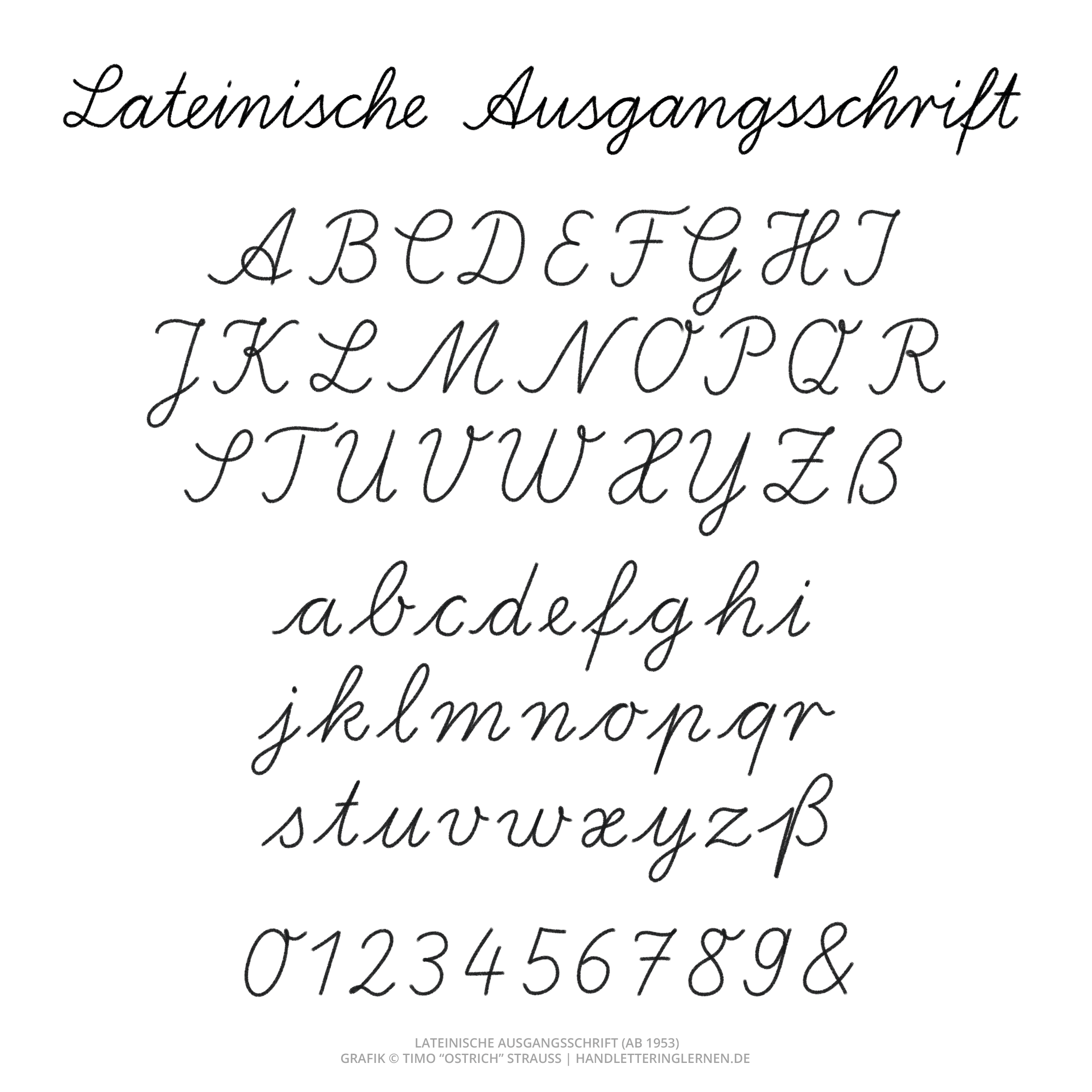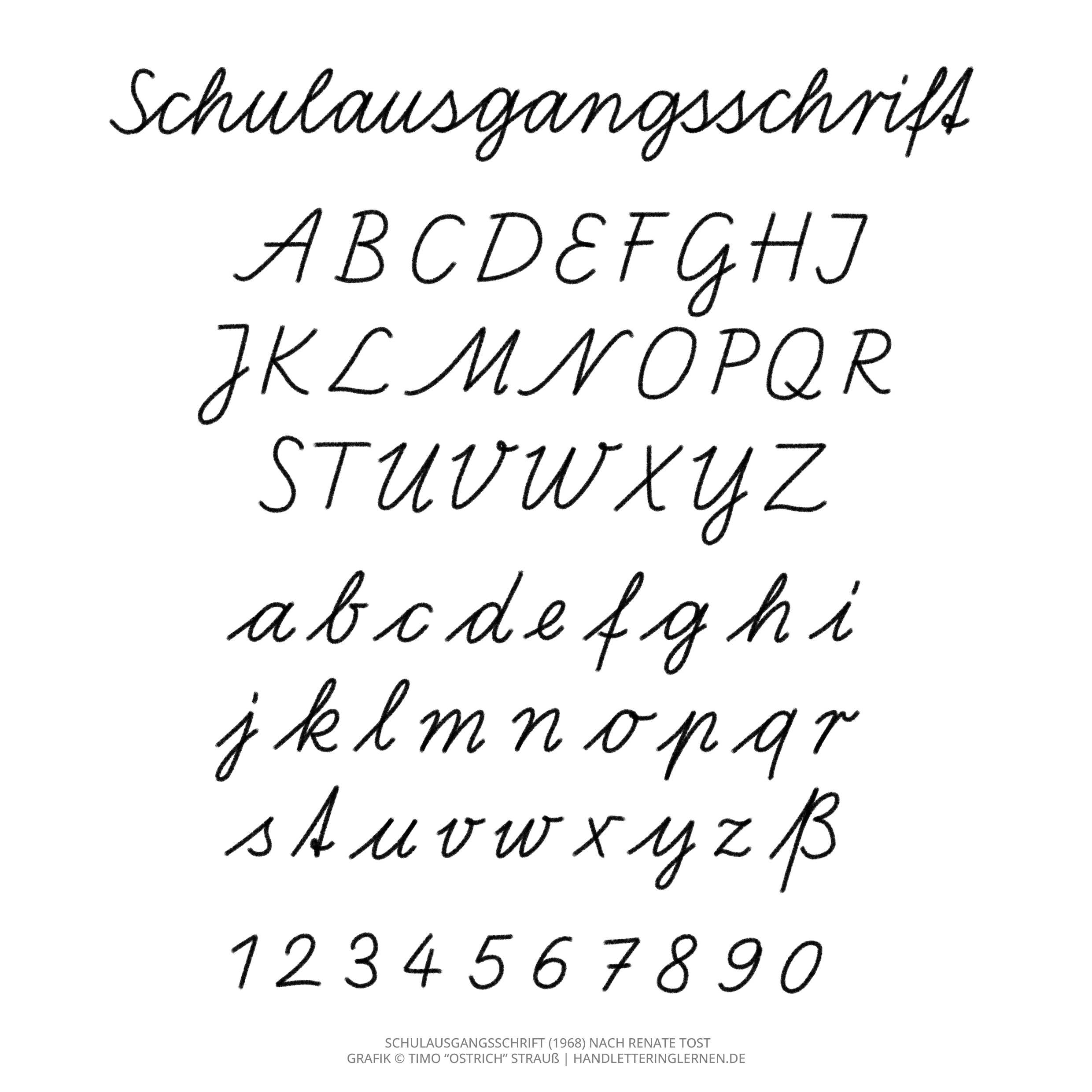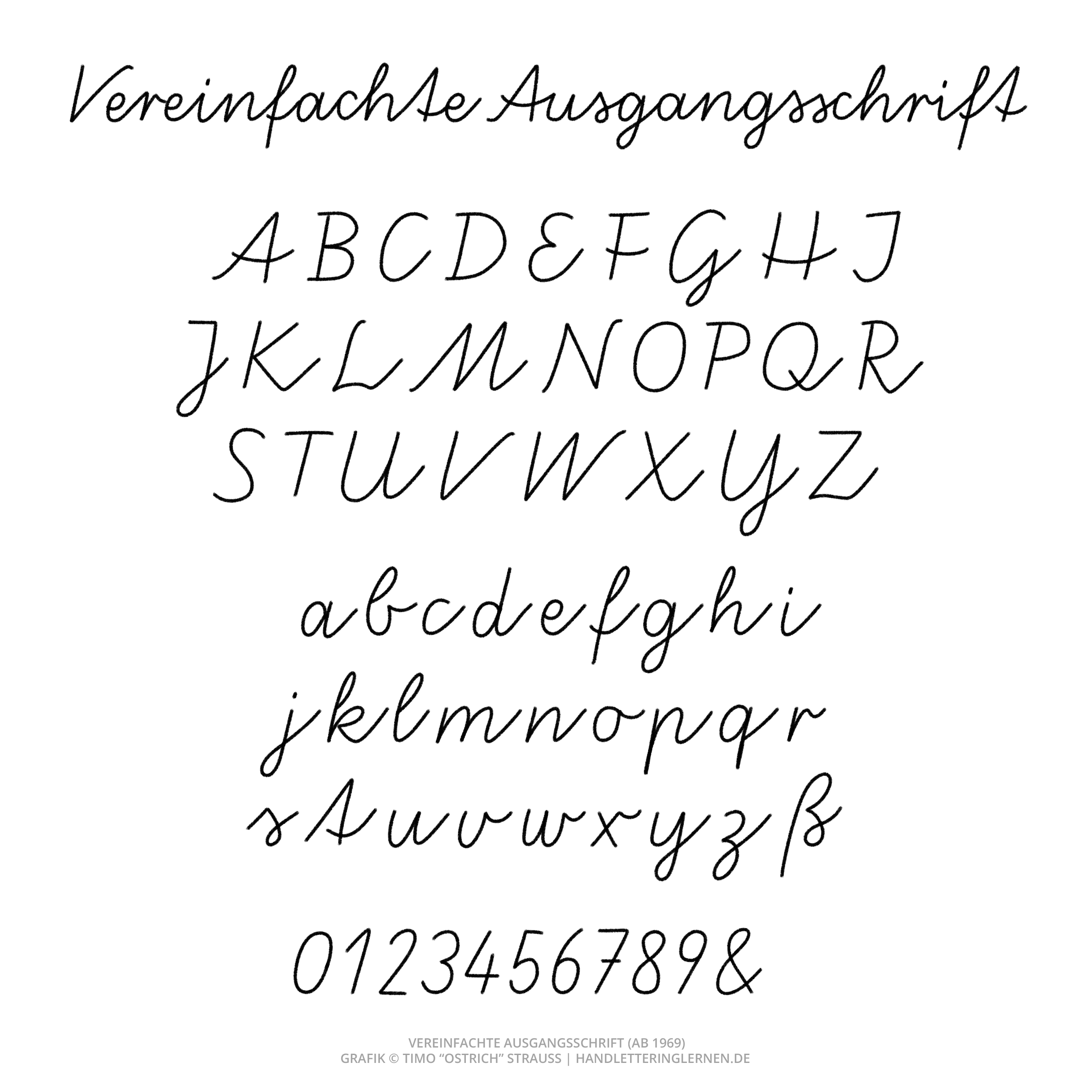
Wie sieht noch gleich das korrekte Schreibschrift-Alphabet aus? Oder ein bestimmter Buchstabe? Diese Frage stellt man sich immer wieder, wenn man nicht regelmäßig eine Schreibschrift schreibt.
Aber Moment mal. DAS eine Schreibschrift Alphabet gibt es gar nicht…
Eine Idee, drei Alphabete
Du hast richtig gelesen. Es gibt nicht nur ein (offizielles) Schreibschrift-Alphabet, sondern gleich mehrere. Welches jetzt das richtige, beste, effektivste ist – darüber lässt sich vortrefflich streiten. 🙂
Und das haben die Bundesländer in der Vergangenheit natürlich auch ausgiebig getan. Ähnliches gilt übrigens auch für die Schweiz und Österreich. Die Schreibschrift-Empfehlungen waren auch dort im stetigen Wandel.
Lateinische Ausgangsschrift (LA)
Die Lateinische Ausgangsschrift wurde aus der Deutschen Normalschrift entwickelt und enthält einige Schlaufen sowie variable Buchstaben-Übergänge.
Ich empfinde die LA als einen Kompromiss aus Ästhetik und Einfachheit.
Vereinfachte Ausgangsschrift (VA)
Bei der Vereinfachten Ausgangsschrift entfielen die meisten Schlaufen zugunsten der Lesbarkeit und Erlernbarkeit.
Optisch näherte sich die VA damit der Druckschrift an. Außerdem werden nahezu alle Buchstaben an der Mittellinie verbunden.
Schulausgangsschrift (SAS)
Die Schulausgangsschrift verfolgt einen ähnlichen Ansatz. Auch hier ähneln die Buchstaben den Druckbuchstaben.
Gleichzeitig wurden die Bewegungsabläufe vereinfacht, damit diese Schreibschrift schneller und fast parallel zur Druckschrift gelernt werden kann.
Wenn man es genau nimmt, ist die Schreibschrift einfach nur eine verbundene Schrift. Sprich: Die Linienführung soll möglichst wenig unterbrochen werden.
Mit dieser Definition wird deutlich, dass es noch unzählige weitere Schreibschrift-Alphabete gibt. Sobald du eines der offiziellen Varianten gelernt hast, kannst du Schreibschriften anderer Künstler adaptieren oder deine eigene Version entwickeln. Letztendlich hat dies auch Einfluss auf deine normale Handschrift.
Eine deutlich komplexere Schreibschrift kann beispielsweise so aussehen, wie die folgende Grafik zeigt.
Dieses Alphabet stammt von Nicole Fally und wurde meinerseits nur in Details verändert.
Ich habe zum Beispiel das große „S“ angepasst, weil ich die gezeigte Variante einfach lieber schreibe. Und genau so, kannst auch du deine eigene Schreibschrift entwickeln.
Die Schreibschrift im Wandel der Zeit
Natürlich gibt es noch viele ältere Variationen unserer Schrift. Wichtig zu erwähnen sind dabei die Deutsche Kurrentschrift, Sütterlin, die Englische Schreibschrift oder die Spencerian Script (USA).
Ich, (Jahrgang 87) schreibe seit fast 30 Jahren nun unverändert in der LA. Genau wie es oben abgedruckt ist. Lediglich das große X habe ich in ein Druckschrift „X“ geändert, da es großen „H“ zu ähnlich sieht und es leichter zu lesen ist. Im Gegensatz zu meinen Schulkammeraden habe ich nie zur Druckschrift gewechselt.
Richtig stark! Jetzt ist das ja ein großer Vorteil, wenn dir die Schrift so aus dem Handgelenk kommt. 🙂
Kurrent fand ich auch immer spannend und sehr schön anzusehen – kannte ich von meinen Großeltern und deren Eltern
ich schreibe immer wenn ich meine, der Empfänger könnte es lesen, in Kurrent. In der Grundschule hatte ich es im Fach „Schönschreiben“ gelernt. Wir mussten in der Grundschule damals parallel „die lateinische und die deutsche Ausgangsschrift“ lernen, letztere = Sütterlin. In beiden Schriften wurden Diktate geschrieben. Aber meine Lieblingsschrift wurde Kurrent.
Hallo zusammen, ich mag das Brushletting sehr, auch die Faux Calligraphy. Gelernt habe ich tatsächlich noch die Kurzschrift (Stenografie). Auch heute macht es mir Spaß, kurze Notizen damit zu schreiben. Leider brauche ich meine Handschrift gar nicht mehr. Ich schreibe auch keine Postkarten, Briefe oder Tagebücher. Mir gefällt es sehr, auf der Tastatur zu schreiben oder den Text zu diktieren. Das Brushlettering und seine Verwandten ist für mich ein schönes Hobby und ein Ausgleich. Ich hole mir dazu auch gerne Ideen auf FB oder Insta. Das Experimentieren macht schön neugierig.
Ich hab damals, 1968, die Lateinische Ausgangsschrift gelernt ! Parallel dazu hatten wir ein Fach „Schönschreiben“ , in dem wir die altdeutsche Schrift, das Sütterlin noch gelernt haben.